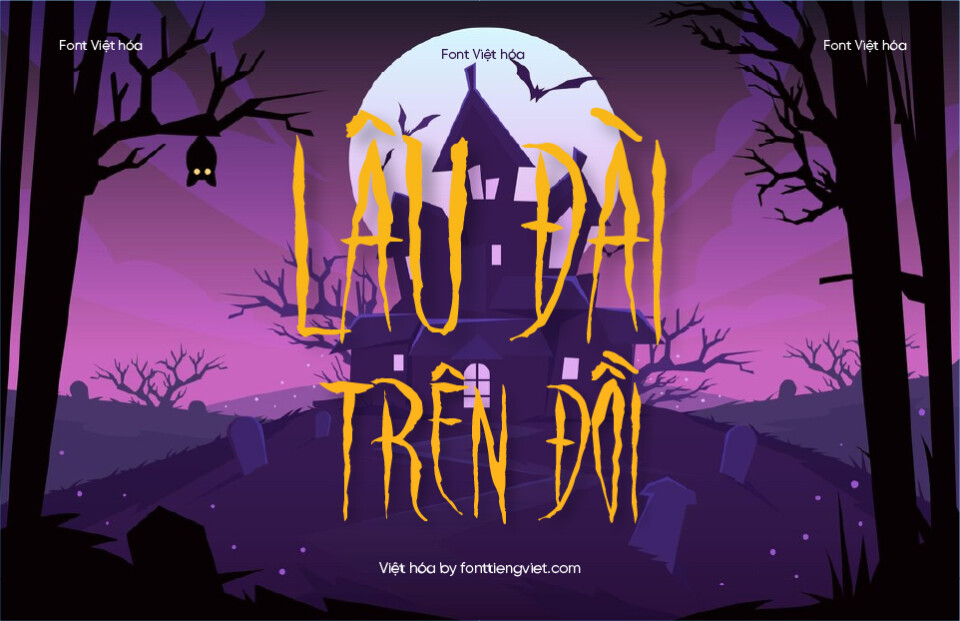
Font Việt hóa 1FTV VIP Raven Song – Font Halloween – Đỉnh Cao Sáng Tạo Kinh Dị
Trong thế giới thiết kế đồ họa hiện đại, việc tìm kiếm một bộ Font Chữ độc đáo để thể hiện tinh thần ma mị của lễ hội hóa trang là điều vô cùng quan trọng. Font Việt hóa 1FTV VIP Raven Song – Font Halloween nổi lên như một lựa chọn hàng đầu nhờ phong cách nghệ thuật đặc trưng, kết hợp giữa sự cổ điển và nét rùng rợn tinh tế. Bộ phông chữ này không chỉ giúp các bạn học sinh dễ dàng tạo ra những tấm thiệp mời ấn tượng mà còn hỗ trợ đắc lực cho các thầy cô trong việc thiết kế tài liệu giảng dạy sinh động về chủ đề văn hóa phương Tây.
Đặc điểm nổi bật của Font Việt hóa 1FTV VIP Raven Song – Font Halloween
Thiết kế đậm chất nghệ thuật ma quái
Bộ Font Việt hóa 1FTV VIP Raven Song – Font Halloween sở hữu những đường nét uốn lượn sắc sảo, mô phỏng hình ảnh bộ móng vuốt của loài quạ hoặc những nhành cây khô trong đêm tối. Điểm đặc biệt của phông chữ này chính là sự cân bằng giữa tính thẩm mỹ và khả năng đọc hiểu, giúp người xem không bị rối mắt dù thiết kế có phần kỳ quái. Các ký tự tiếng Việt được xử lý chỉn chu, đảm bảo không bị lỗi dấu, mang lại sự chuyên nghiệp tối đa cho mọi sản phẩm thiết kế từ poster đến banner sự kiện.
Ứng dụng đa dạng trong giáo dục và thiết kế
Với bộ Font Việt hóa 1FTV VIP Raven Song – Font Halloween, người dùng có thể thỏa sức sáng tạo trên nhiều nền tảng khác nhau. Đối với môi trường học đường, phông chữ này cực kỳ phù hợp để trang trí báo tường, làm slide thuyết trình hoặc thiết kế các trò chơi tương tác trong dịp lễ hội tháng Mười. Sự linh hoạt trong định dạng cho phép font hiển thị sắc nét trên cả màn hình kỹ thuật số lẫn bản in truyền thống.
Kết luận về bộ phông chữ Raven Song
Việc sử dụng Font Việt hóa 1FTV VIP Raven Song – Font Halloween sẽ mang lại làn gió mới cho các dự án sáng tạo của bạn, giúp thông điệp truyền tải trở nên cuốn hút và đầy cá tính. Hãy bắt đầu khám phá thế giới Font Miễn Phí, Font Việt Hóa, Font Việt hóa 1FTV VIP Raven Song – Font Halloween ngay hôm nay để nâng tầm thẩm mỹ cho mọi tác phẩm thiết kế của mình một cách dễ dàng và hiệu quả nhất.